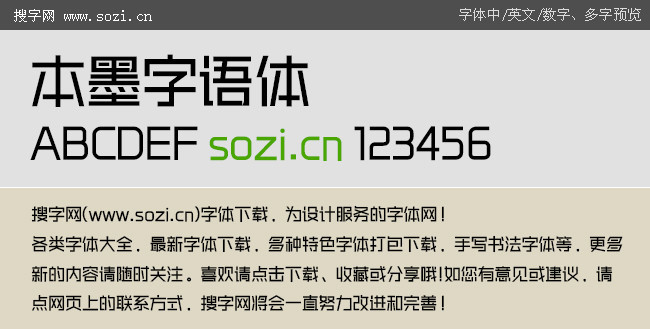
本墨字語(yǔ)體
搜字網(wǎng)提供一款本墨字語(yǔ)體中文藝術(shù)字體下載,本墨字語(yǔ)體在構(gòu)造上兼具本墨詠黑和本墨陳黑的字體特色,字跡深沉而莊嚴(yán),適用于嚴(yán)謹(jǐn)內(nèi)容或重要文字通知,給人清晰直觀的視覺(jué)呈現(xiàn)。適用于書(shū)籍設(shè)計(jì)、報(bào)紙標(biāo)題、畫(huà)冊(cè)設(shè)計(jì),網(wǎng)頁(yè)設(shè)計(jì)等應(yīng)用。